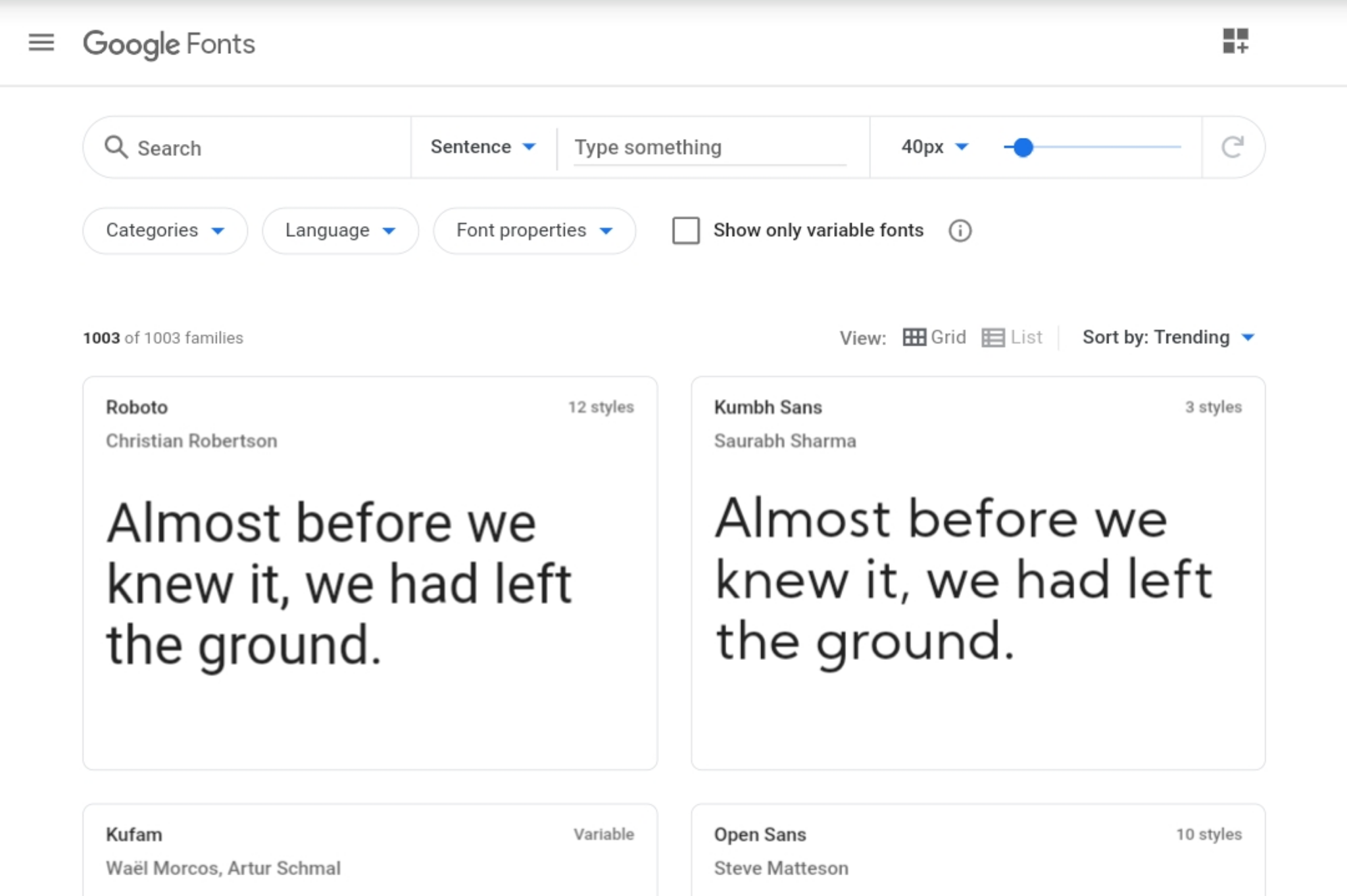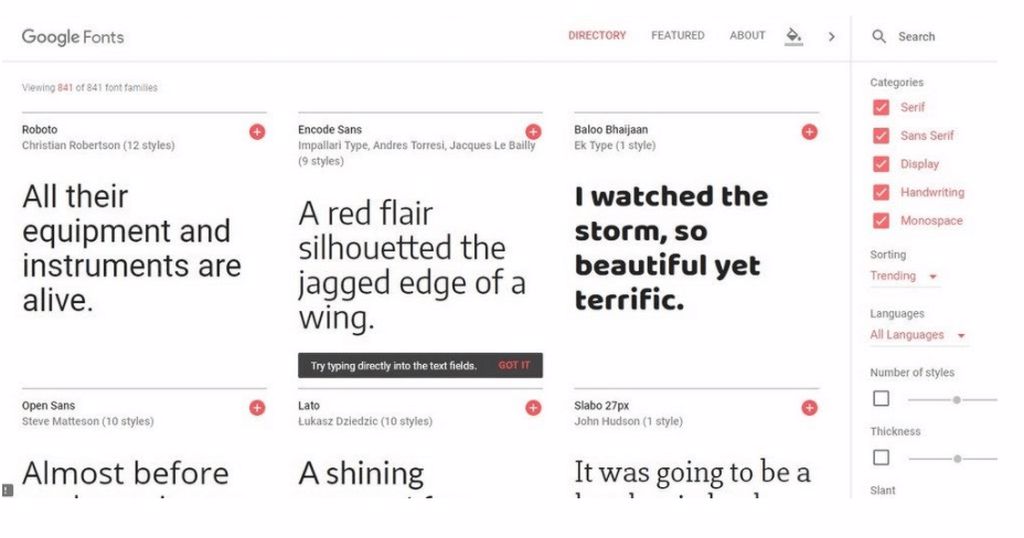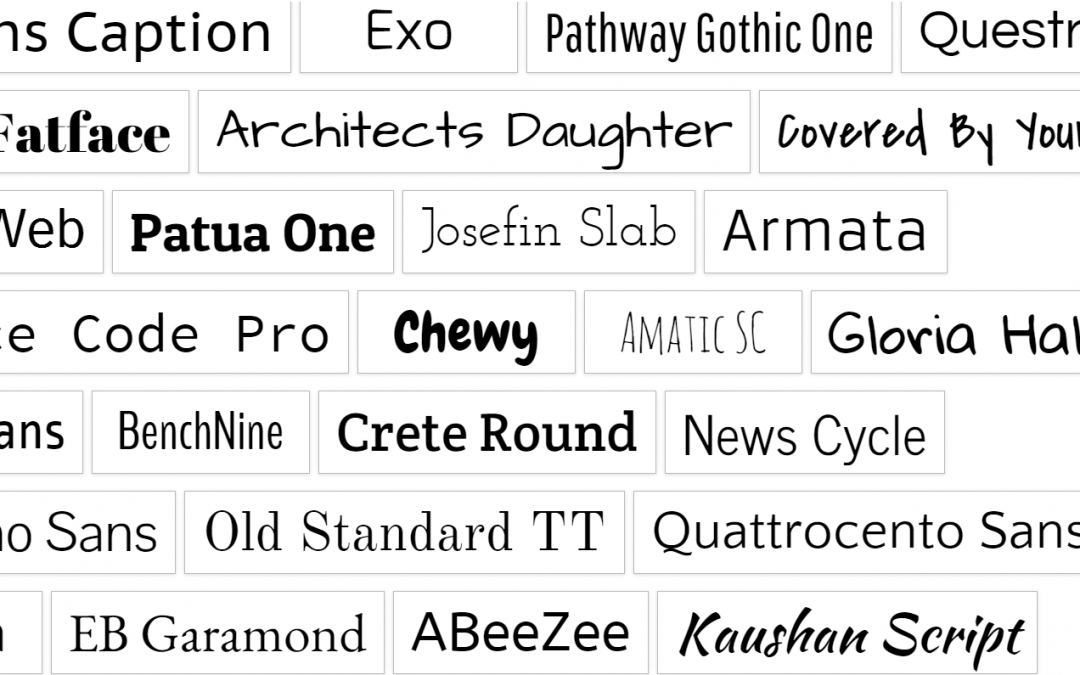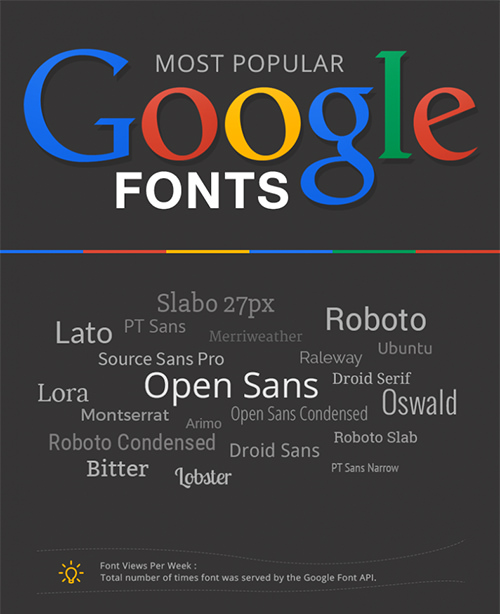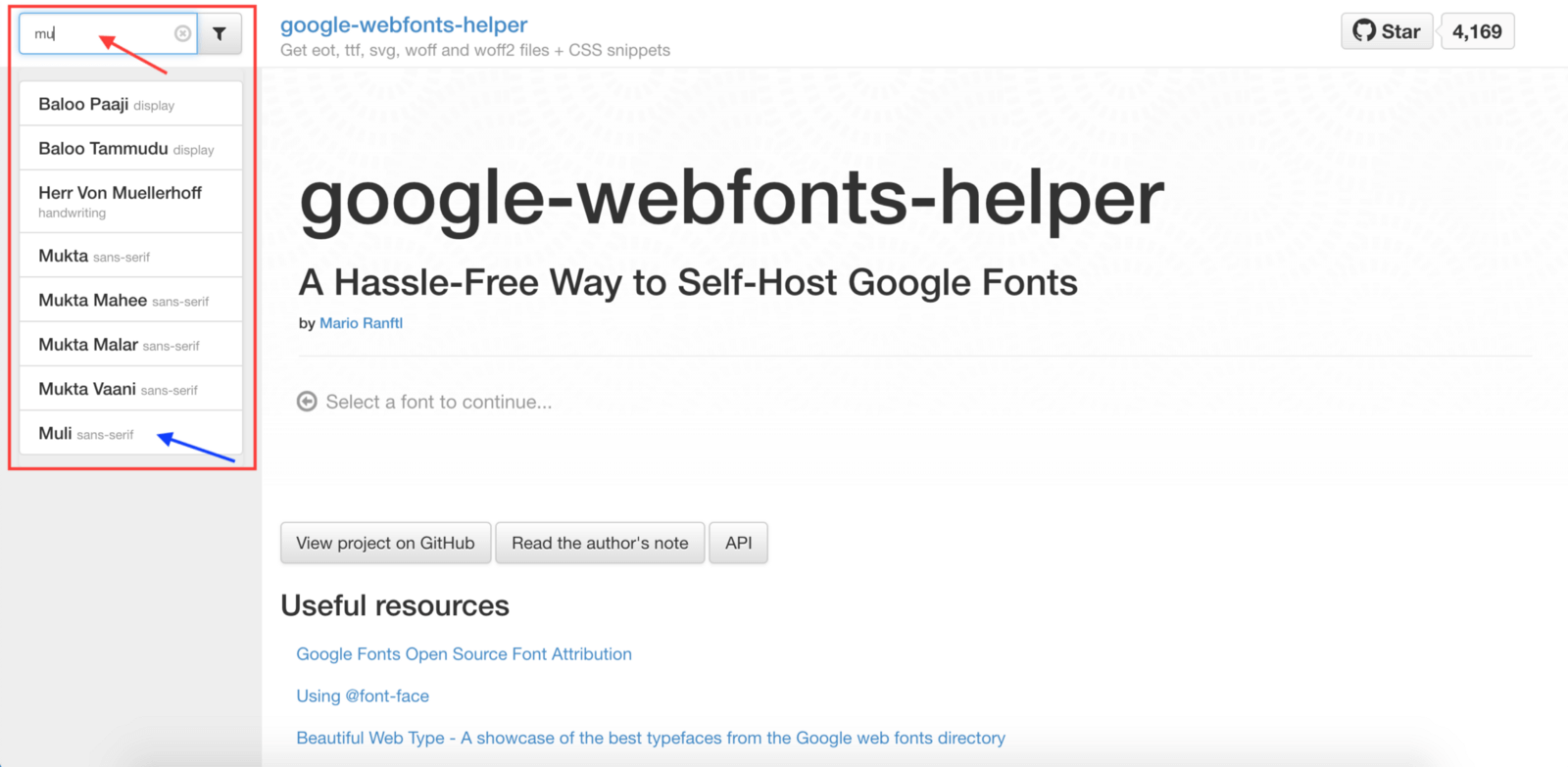
10 недооцененных бесплатных Google шрифтов без засечек
Google Fonts – огромный ресурс, но мы видим одни и те же шрифты в тысячах проектов.
В этой статье предлагаем вам тщательно отобранный список из 10 привлекательных, но мало используемых шрифтов без засечек, которые доступны бесплатно в библиотеке шрифтов Google.
1. DM Sans
Дизайнеры: Colophon Foundry, Jonny Pinhorn, Indian Type Foundry
Описание: DM Sans – это малоконтрастный геометрический шрифт без засечек, предназначенный для использования с меньшими размерами текста.
2. Lexend
Дизайнеры: Bonnie Shaver-Troup, Thomas Jockin, Santiago Orozco, Héctor Gómez
Описание: Lexend первоначально спроектирован с учетом читателей, страдающих дислексией и другими проблемами чтения. Он предназначен для снижения зрительного стресса и улучшения навыков чтения.
3. Chakra Petch
Дизайнер: Cadson Demak
Описание: Chakra Petch – квадратный шрифт без засечек с сужающимися углами, поддерживающий как тайский, так и латинский алфавит.
4. IBM Plex Sans
Дизайнеры: Mike Abbink, Bold Monday
Описание: IBM Plex Sans – нейтральный, но дружелюбный гротеск без засечек, входящий в суперсемейство IBM Plex (содержащие также IBM Plex Serif и IBM Plex Mono).
5. Space Grotesk
Дизайнер: Florian Karsten
Описание: Space Grotesk – это вариант пропорционального шрифта без засечек, основанный на семействе шрифтов фиксированной ширины Space Mono от Colophon Foundry.
6. Balsamiq Sans
Дизайнер: Michael Angeles
Описание:
Balsamiq Sans – это рукописный шрифт без засечек, изначально созданный для инструмента создания вайрфреймов Balsamiq.
7. Questrial
Дизайнеры: Joe Prince, Laura Meseguer
Описание: Questrial – это геометрический шрифт без засечек с добавлением гротескного оттенка.
8. Epilogue
Дизайнеры: Tyler Finck, ETC
Описание: Epilogue представляет собой переменный шрифт без засечек с осью веса, девятью весами и курсивом.
9. Archivo
Дизайнеры: Héctor Gatti, Omnibus Type
Описание: Archivo – гротескный шрифт без засечек, напоминающий американские шрифты конца девятнадцатого века.
10. Sen
Дизайнер: Kosal Sen
Описание: Sen – это шрифт без засечек геометрической формы с разумным и дружелюбным внешним видом.
Google Fonts – библиотека современных шрифтов, оптимизированных под веб-сайты.
Если вы устали от набивших оскомину базовых шрифтов, предустановленных на вашем компьютере, и хотели бы приятно выделиться на фоне конкурентов, то библиотека шрифтов Google Fonts предлагает такую возможность. Совершенно бесплатно.
Прежде, чем приступить к выбору шрифта, рекомендуем посмотреть, какими шрифтами пользуются ваши конкуренты, а также ведущие бренды вашей сферы. Первое поможет избежать вам повторений и действительно выгодно выделиться на фоне прочих игроков рынка, а второе – воодушевиться новыми идеями.
Выбор шрифта
Общий вид на страницу выбора шрифтов Google FontsЧтобы начать выбор шрифта, перейдите на сайт Google Fonts и выберите в главном меню Fonts (Шрифты). В графе Type something можно задать желаемое слово, например, название вашей компании.
Эта функция позволит вам сразу увидеть, как будет выглядеть слово, набитое тем или иным шрифтом.
Типы шрифтов
Выбор категории шрифта из выпадающего менюШрифты можно легко фильтровать. Для сортировки выберите выпадающее меню Categories (Категории), а затем проставьте галочки в те пункты, которые вам нужны.
Serif – шрифты с засечками, Sans Serif – без засечек, Display – экранный шрифт, то есть шрифт для заголовков, Handwriting – рукописный, Monotype – моноширинный шрифт, в котором все знаки имеют одинаковую ширину.
Кириллица
Выбор кириллических шрифтовЕсли вам нужен шрифт, который работает также в кириллице, например, для использования на двуязычном сайте, то обязательно выберите в графе Language (Язык) пункт Cyrillic или Cyrillic Extended.
Не все шрифты Google Fonts имеют русскоязычные версии. Поэтому использование названных выше фильтров позволит вам отсеять уже на этапе подбора шрифта такие, где нет возможности применения кириллицы.